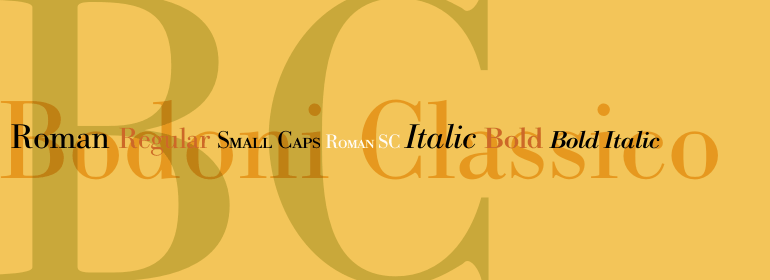
Bodoni Classico™
Bodoni Classico™,这款字体结构工整、笔画清晰,兼顾美观与易读性,适用于标题、正文、海报、包装、LOGO 等多种场景。字形优雅稳定,风格百搭耐看,适配日常排版与创意设计,让文字呈现更舒适、更具质感。Bodoni Classico™一笔一画,皆是细节,以均衡的比例、流畅的线条打造舒适视觉体验,字形端正大气,风格简约现代。无论是商业设计、品牌宣传还是日常排版,都能轻松驾驭,让文字更有格调与力量。Bodoni Classico™字体下载。
字体品牌: Linotype(Monotype) 设计师:Luin,Franko 字体分类:衬线体、正文字体 字体属性:外文 字符集:Unicode 发布时间: 2018